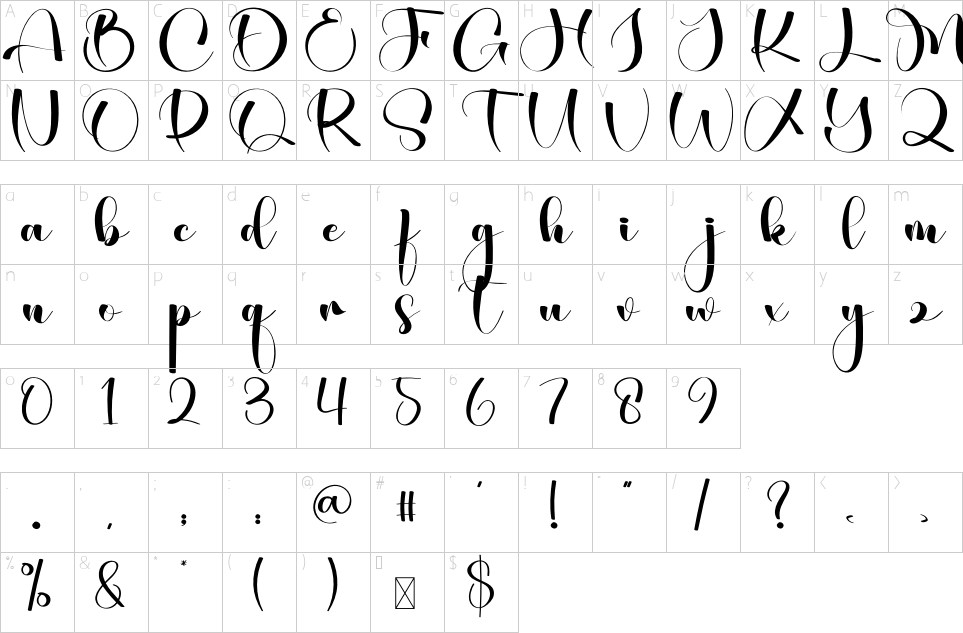
Galery Christmas Font – Download Grátis
A Galery Christmas é uma fonte única e encantadora que está aqui para deixar sua obra de arte digital mais doce e festiva durante as férias. Ela foi criada por um designer anônimo, mas a traz até você no formato tanto para Windows quanto para Mac. Com seu design delicado e detalhado, ela é perfeita para decorar textos natalinos ou qualquer obra de arte que precise de uma pitada de magia nesta época do ano especial. Seu download foi baixado 258 vezes, um número que prova sua popularidade entre os criadores de conteúdo online e designers de ícones. Invista em agradar seus espectadores com essa fonte encantadora durante as festividades natalinas.